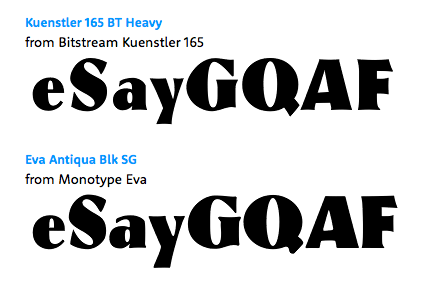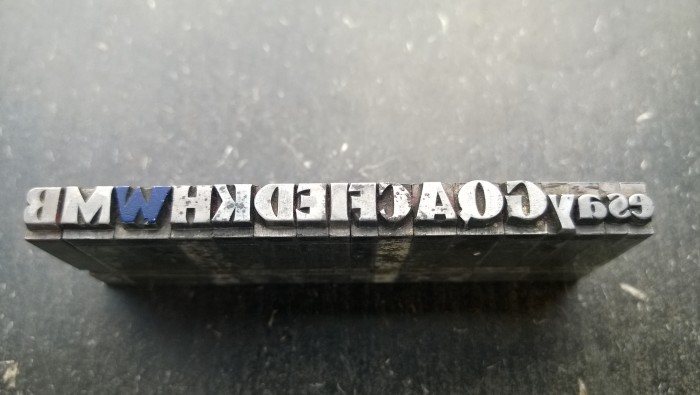
alte Bleisatz-Schrift 16pt - wie heisst sie?
vor einigen Monaten habe ich die kleine Druckerei meines Vaters geerbt (mit ein paar Schränken Bleisatz und einer 73er Korrex). Ich habe nun in den letzten Monaten viele Schriften betitelt, sortiert und verschaffe mir einen Einblick in dieses für mich neue Thema.
Ich habe eine Schrift, die ich nicht zuordnen kann. Siehe Foto. Leider habe ich keinen Abzug davon, aber vielleicht könnt Ihr es anhand des Fotos erkennen. Ich finde das große W und das kleine y sehr ungewöhnlich (mal abgesehen davon, dass das W kaputt und blau gefärbt ist).
Kann jemand diese Schrift zuordnen? Wie heisst sie?
"Kuenstler 165" oder "Eva Antiqua" heißen sie heute …
Früher hiess sie dann wohl "fette Koch-Antiqua".